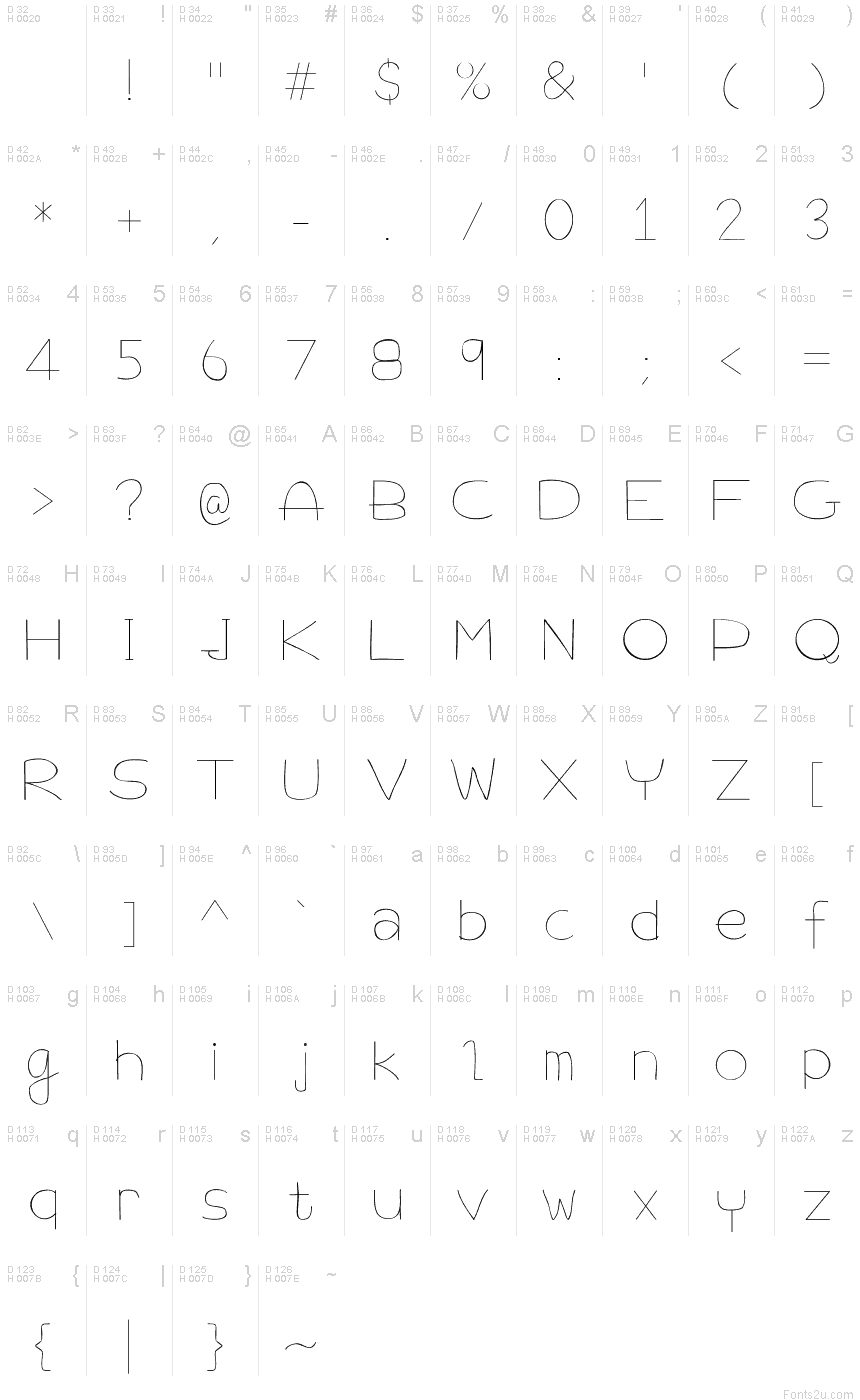
Impossible to odręczny krój pisma, który wygląda, jakby został narysowany jednym, niezwykle cienkim drucikiem. Litery są wysokie i pełne lekkości, o niezwykle cienkich liniach i szerokich, kolistych kształtach, które nadają każdemu słowu delikatny, niemal nieważki charakter. Całość sprawia wrażenie minimalistycznej i nieco fantazyjnej – jak notatki skreślone przez skrupulatnego marzyciela.
Dzięki Impossible nagłówki i logotypy zyskują miękki, wyrafinowany charakter, który wciąż pozostaje osobisty. Ten bezpłatny font świetnie sprawdza się w brandingu modowym, na opakowaniach kosmetyków, w grafikach z cytatami, na okładkach portfolio, papeterii ślubnej i minimalistycznych plakatach. Stosuj go w dużym rozmiarze, aby utrzymać ostrość cienkich linii, a w tekście głównym połącz Impossible z czystym, geometrycznym krojem bezszeryfowym, aby zakotwiczyć jego lekki, ulotny urok.
Impossible